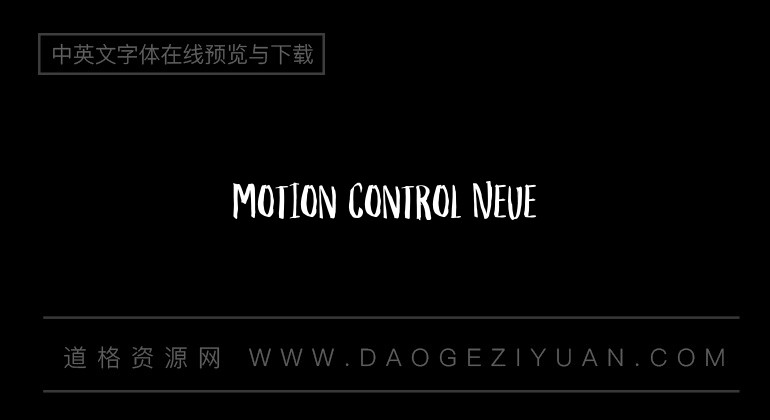
? Motion Control Neue 是一款由 Monotype 公司开发的字体,它是一款现代化的紧凑型字体,可以提供清晰的文本和图形,并具有极佳的可读性。它的特点是紧凑的设计,让文本在屏幕上看起来更加清晰,从而提高可读性。它的字母形状与传统的字体有很大的不同,可以更好地提供新颖的视觉效果,并且可以让文本在屏幕上看起来更加美观。内容介绍
Motion Control Neue是一款非常不错的手写艺术字体,具有很好的视觉感,适合于文化类的宣传设计、商业类品牌的广告和产品包装设计以及个性化文字排版等较多场景。